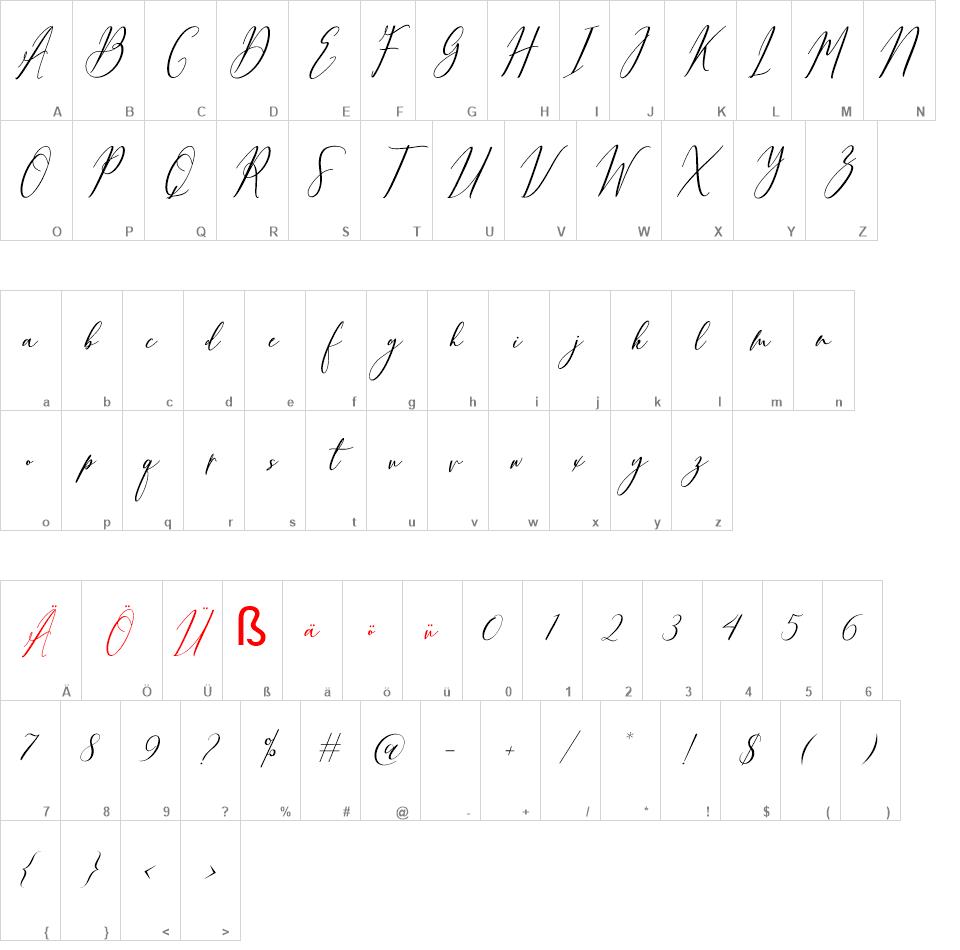
Bellindia
Bellindia  font
Bellindia
Bellindia Script ist eine moderne Kalligraphie Schrift mit der aktuellen Handschrift Stil, diese Schrift ist perfekt für Branding, Hochzeit Einladungen, Zeitschriften, Tassen, Visitenkarten, Zitate, Plakate und vieles mehr, können Sie zuerst versuchen, wenn Sie diese Schriftart kaufen möchten.
Bellindia Script ist mit 340 Zeichen ausgestattet. Und indem Sie viele dieser Glyphen haben, können Sie die Buchstaben nach Ihren Wünschen auswählen, viele Variationen und Optionen für jeden Buchstaben, so dass Sie Ihre Design-Entscheidungen anpassen können.